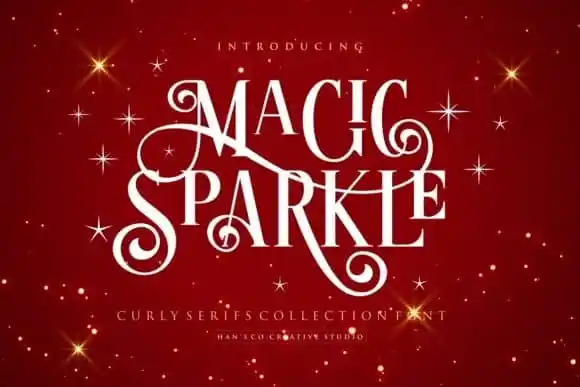
Magic Sparkle Display Font – Download Grátis
A Magic Sparkle Display Font é uma elegante escolha para qualquer projeto que busque destaque visual. Inspirada nos antigos selos e logotipos vintage, essa fonte all-caps com traçado serifizado apresenta um toque mágico e convidativo. Ideal para estilos de design como publicidade, branding ou editoração de revistas, ela transformará qualquer projeto invernal em algo realmente chamativo e memorável. Com seu traço curvilíneo e sua personalidade encantada, essa fonte oferece uma combinação única de classe clássica e criatividade moderna para qualquer trabalho que você estiver trabalhando. Seja um logotipo, cartaz ou até mesmo um texto simples no site, a Magic Sparkle Display Font é definitivamente o elemento diferenciador que seu design precisa.